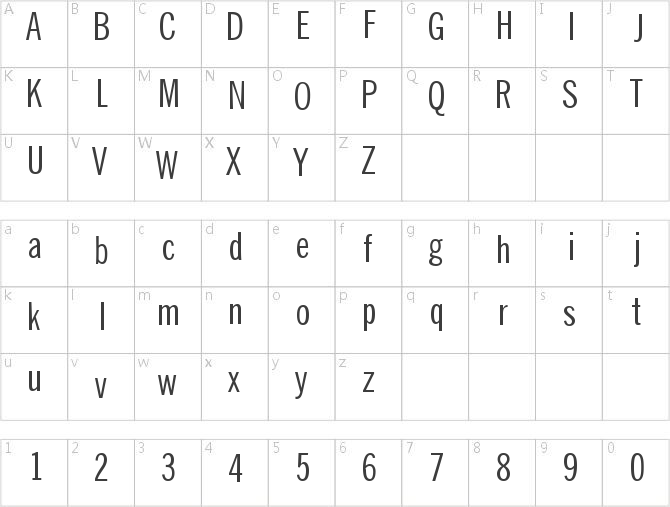
字體名稱(chēng): NobbiGC
NobbiGConDB字體字庫(kù)是一款讓人賞心悅目、百看不厭的英文字體,適合各類(lèi)廣告和產(chǎn)品包裝設(shè)計(jì)應(yīng)用,字體大小0.04MB,格式為ttf字體,上傳用戶(hù)是九醬,作者/版權(quán)方為未知